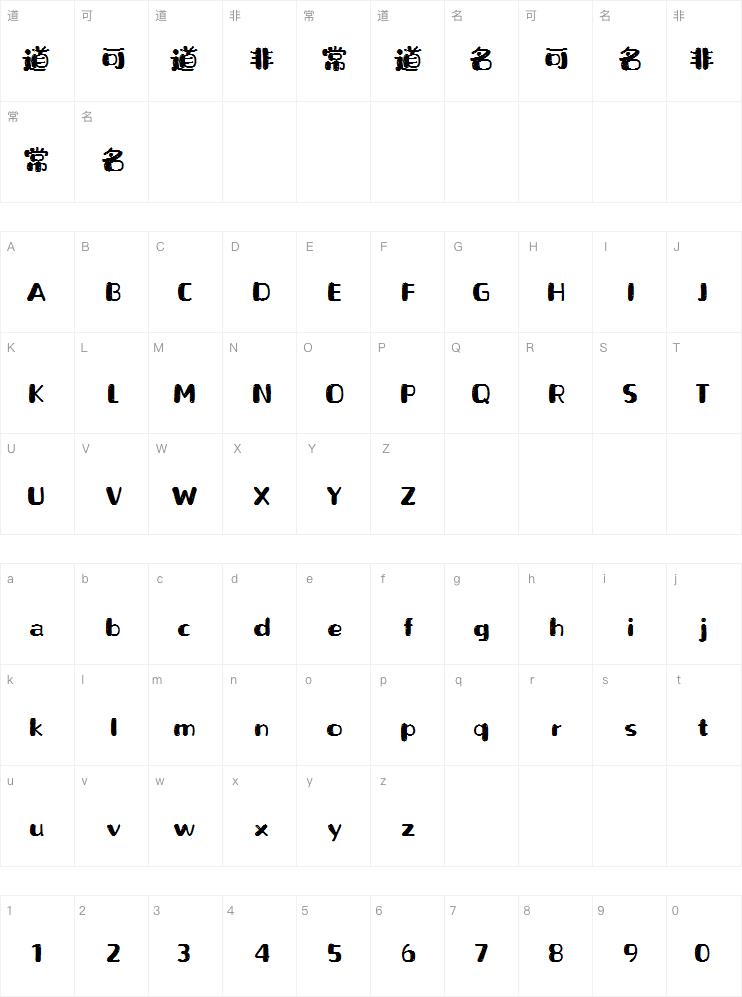
山海蜡笔小熊,是一款全新的字体,包含汉字9169个,符号200+个。该字体是一款手绘风卡通字体,该字体字形灵动多变,童趣可爱,同时融入手绘风笔画造型,整体笔触圆润,活泼清新,从而使得该字体字形灵动多变,在灵动的同时而又极富俏皮感,具有灵活的适用性,天真俏皮又不失时尚感。似蜡笔笔触的手绘风效果使字体的气息更加新奇,笔画间的关系密不可分,同时也增加了字体的自由洒脱之感。结构多变灵动,字形活泼清新,造型生动有趣,具有灵活的适用性,天真俏皮又不失时尚感。该字体字形随笔画多少、结构布局不同而大小不一,各个字的大小随字形的不同而呈现不同的大小,但是在变化中寻求平衡,使得整个字体更具有手写感的温度和节奏感,整体笔触圆润。灵动笔画贯穿笔画始终,内涵丰富,弧度柔和,撇笔平缓舒展,尽显俏皮灵动。